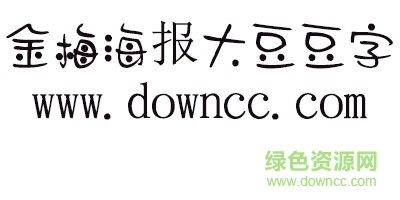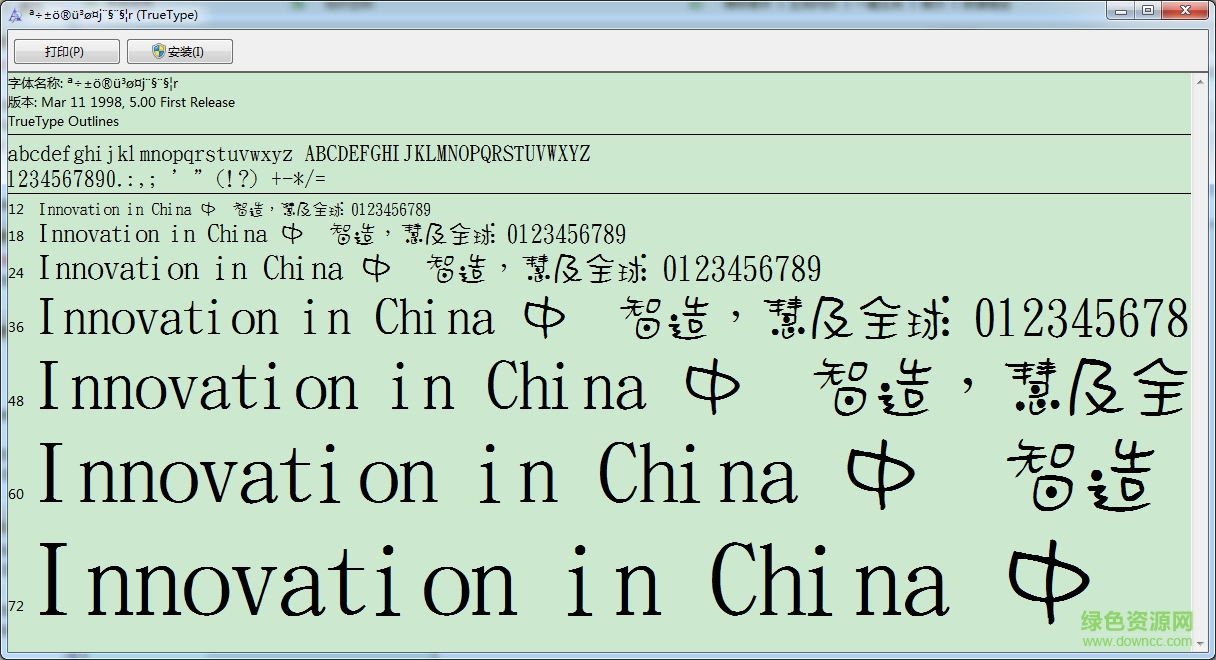
金梅海報大豆豆字體風(fēng)格比較卡哇伊。這款字體多用于設(shè)計一些卡通風(fēng)格的海報、宣傳冊等。能夠在大多數(shù)系統(tǒng)上安裝使用。喜歡豆豆體的朋友快來下載安裝吧。
金梅海報大豆豆字是一款非??蓯鄣?a href="http://m.lz0519.com/k/jinmeiziti/" target="_blank">金梅字體,這款字體上帶小豆豆形狀,看上去非常的美觀,有特色,非常適用于藝術(shù)設(shè)計方面,有需要的朋友歡迎來綠色資源網(wǎng)下載使用!